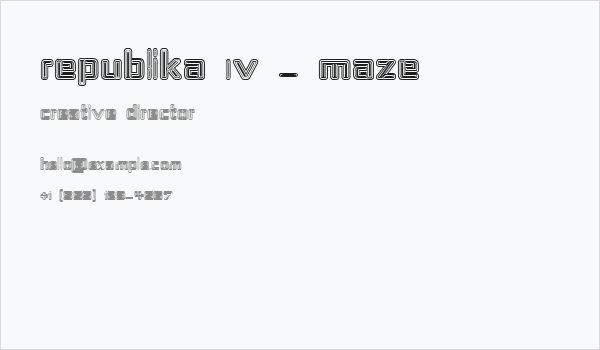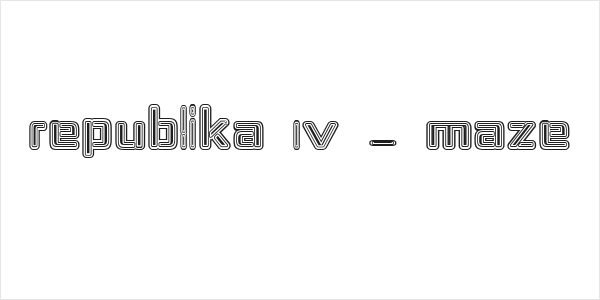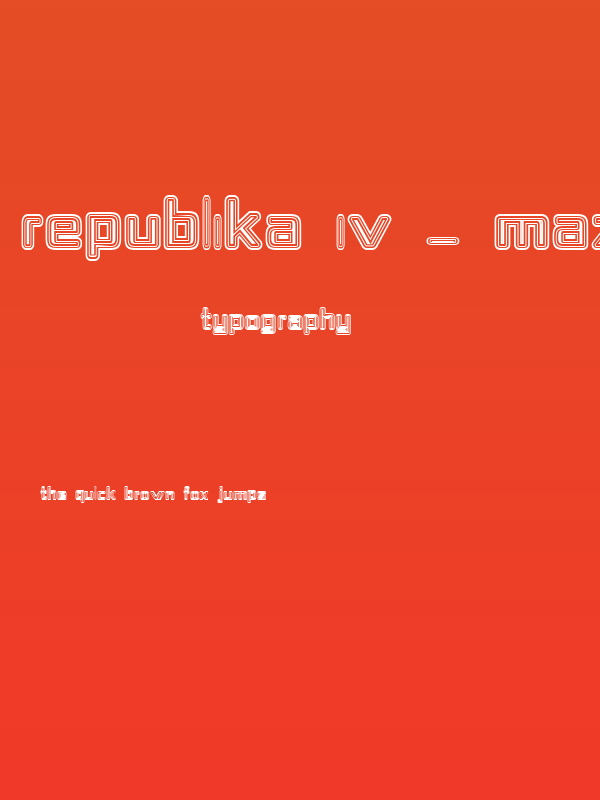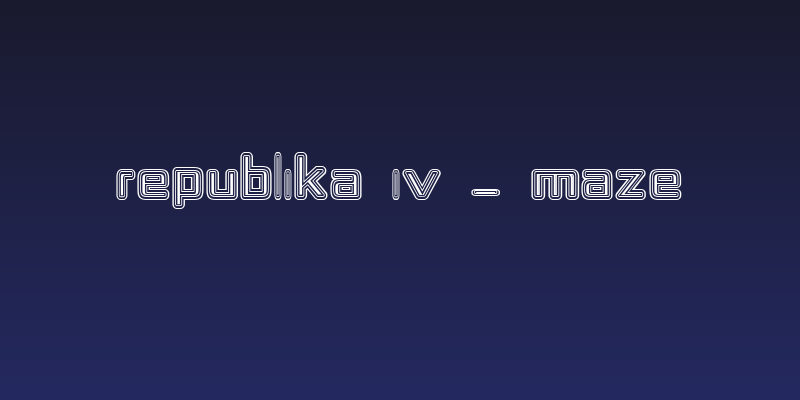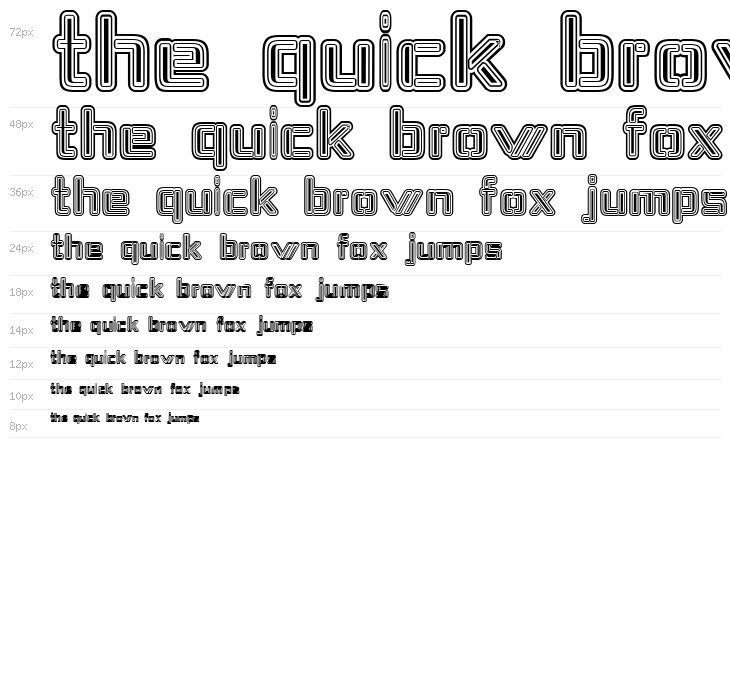
Republika IV - Maze Font
| Stile generale | Futuristic, Retro |
| Progetti proposti | Ideal for projects that require a standout display font, such as posters, album covers, video game titles, or branding for tech and entertainment industries. |